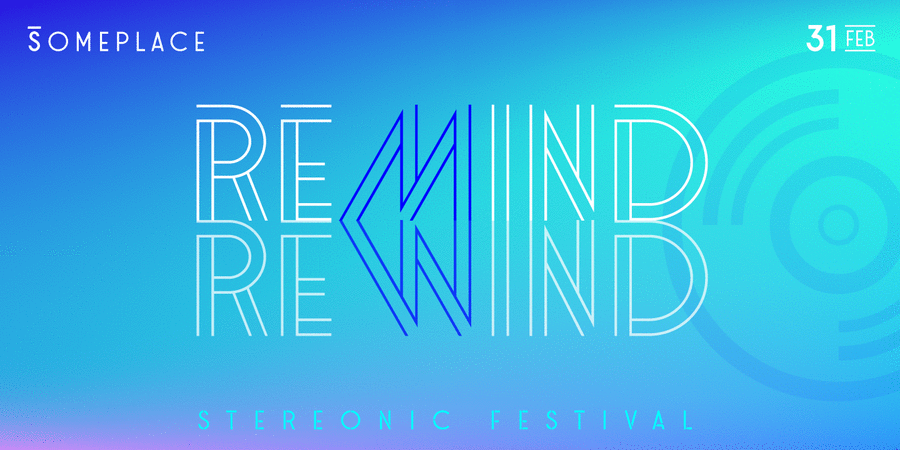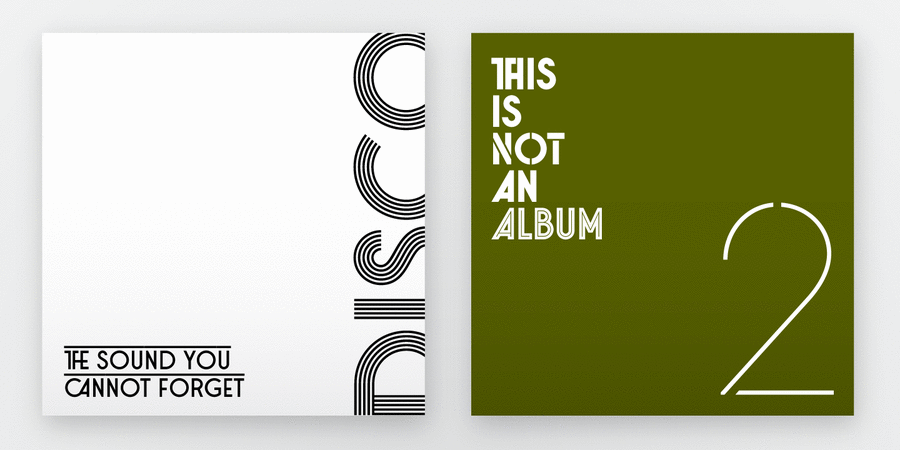
Stereonic – геометричний акцидентний гротеск з елементами арт-деко. 5 насиченостей представлені 38-ма накресленнями, що дозволяють передавати характер різних періодів від 1970-х до 2000-х років. Первісне призначення цієї гарнітури – музичні постери, але вона також здатна додати виразності журналам та неперіодичним виданням. Stereonic також добре працює в якості основи для логотипів завдяки великій кількості альтернатив та лігатур.
Шрифт розробив Олег Ліщук у студії Mint Type у 2018 році.
Особливості сімейства шрифтів StereonicХіт десятиліття:
Асоціації з сімейством шрифтів StereonicОсобистість і характер гарнітури:
чистий, легкий, модний, тонкий, ясний, оригінальний, лаконічний, якісний, дзвінкий, артистичний, сучасний, міський, музичний, популярний, точний, дорогий, мінімалістичний, делікатний, прохолодний, ефектний, невагомий, прозорий, інтимний, крихкий, повітряний, скляний, гострий, дротяний, холодний, рівний, електронний, худий, виразний, молодіжний, свіжий, твердий, чіткий, пульсуючий, неоновий, яскравий, клубний, сексуальний, манірний, дотепний, грайливий, глянцевий, гламурний, позитивний, тусовочний, ритмічний, святковий, привабливий, танцювальний, мерехтливий, нічний, Простий, елементарний, креслярський, логічний, стійкий, кислотний, психоделічний, ламповий, теплий, грубий, помітний, мотивуючий, інженерний, архітектурний, хіпстерський, дерев'яний, радісний, вінтажний, переконливий, стабільний, серйозний, надійний, впевнений, сильний, індустріальний, техногенний, статичний, гучний, урбаністичний, сталевий, міцний, штучний, машинний, залізничний, амбітний, суворий, робочий, мужній, брутальний, кричущий, важливий, монументальний, важкий, потужний, солідний, промисловий, активний, радянський, жорсткий, динамічний